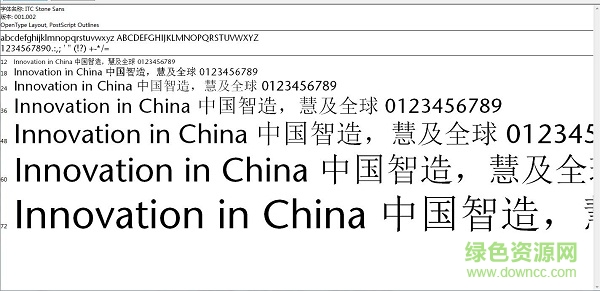
itc stone sans字體包收錄了medium、bold以及regular三種字型,這套字體線條曲率相同,粗細(xì)相當(dāng),圓弧流暢,易讀性強(qiáng),為無(wú)襯線字體,喜歡的朋友歡迎免費(fèi)下載!
無(wú)襯線的字體結(jié)構(gòu)簡(jiǎn)單,在同等字號(hào)下,無(wú)襯線的字體看上去要比有襯線的更大,結(jié)構(gòu)也更清晰,所以電子設(shè)備的屏幕上也偏好使用無(wú)襯線字體